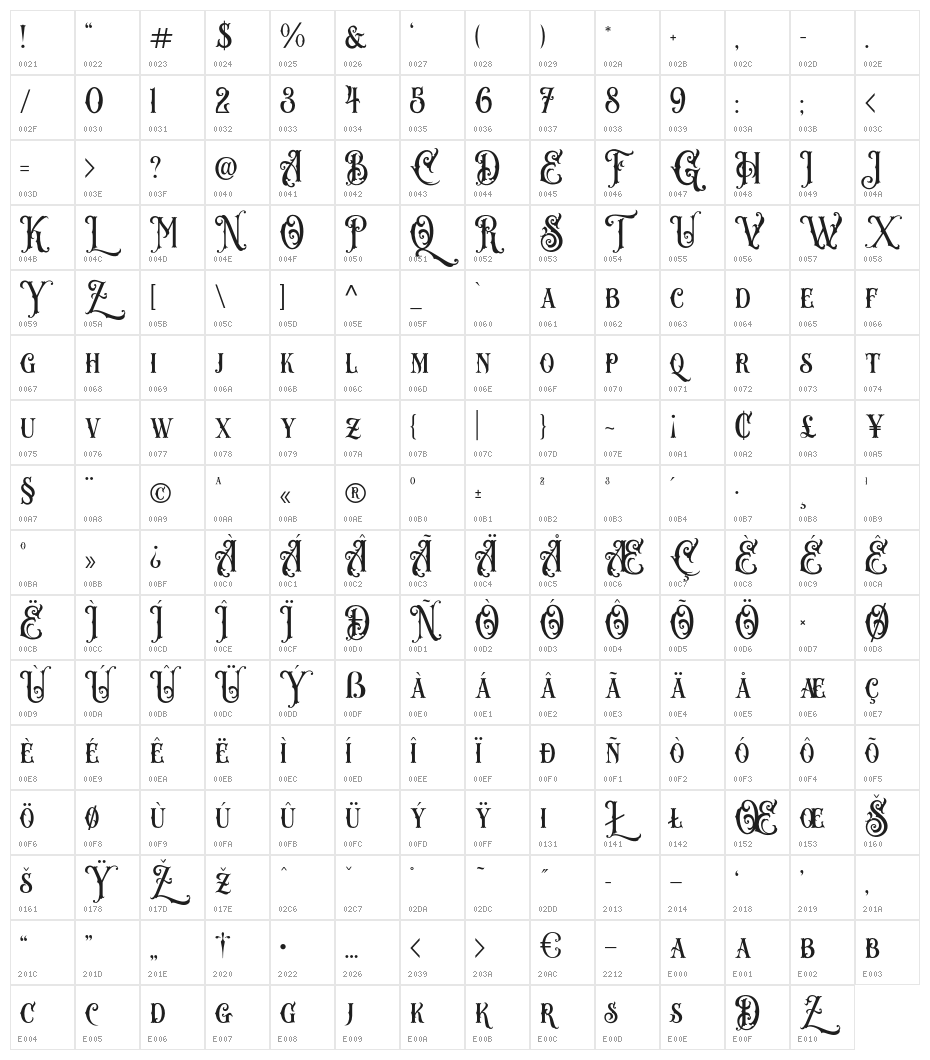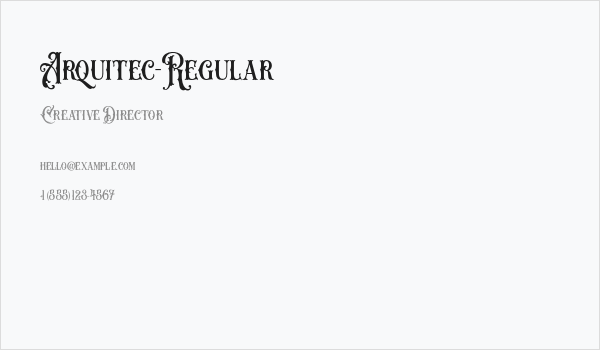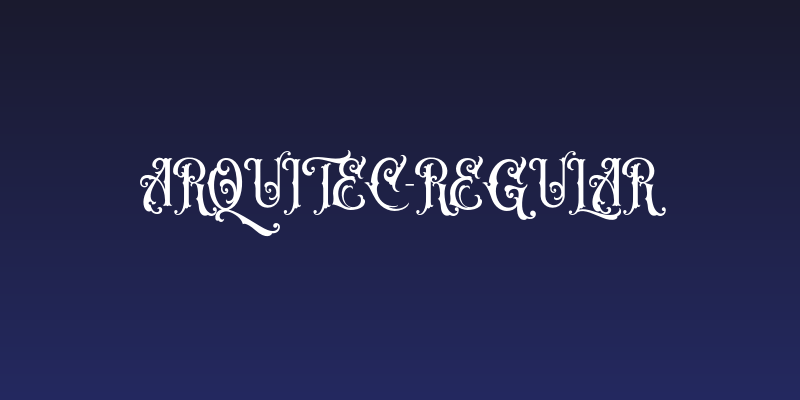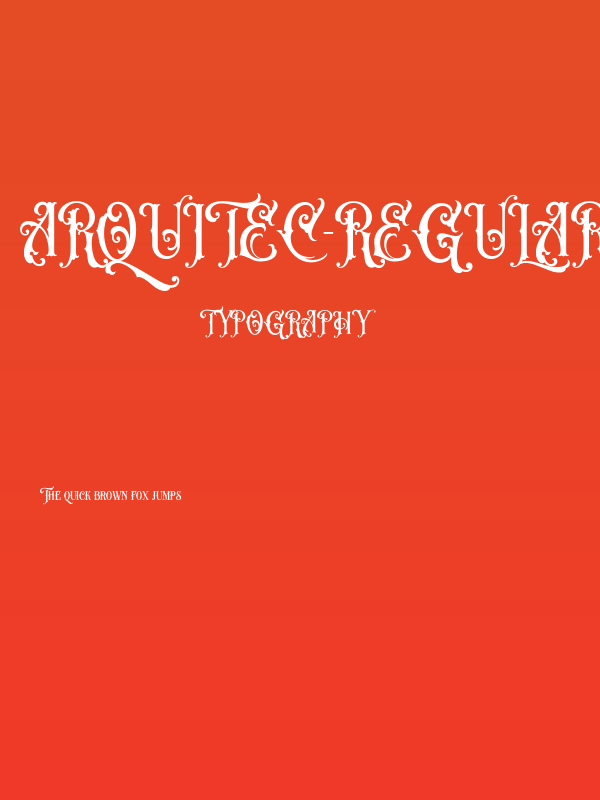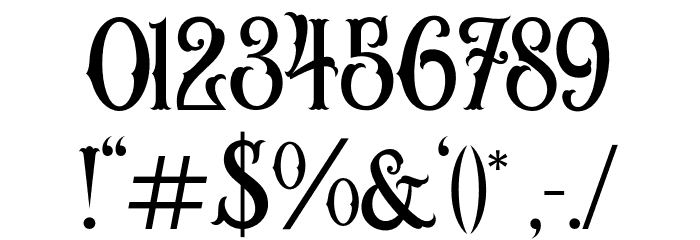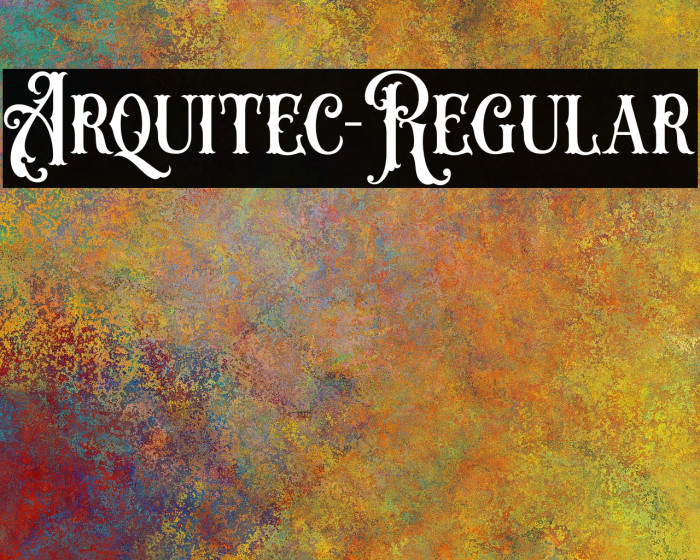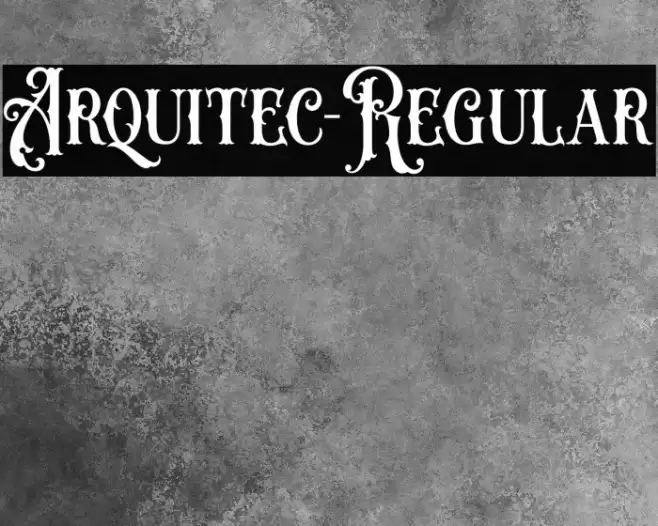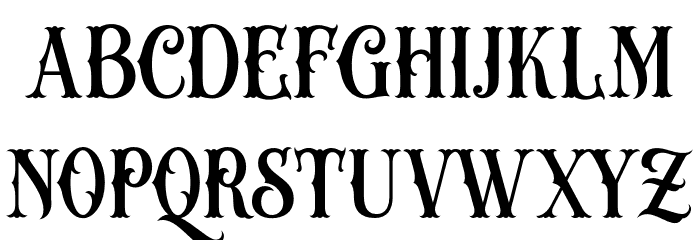
Arquitec-Regular Font
✎ Curly
| Categorie | Curly |
| Caso d'uso | Headlines, Logos, Artistic displays |
| Progetti proposti | Ideal for wedding invitations, event posters, branding for luxury products, or any project requiring a touch of elegance and sophistication. |